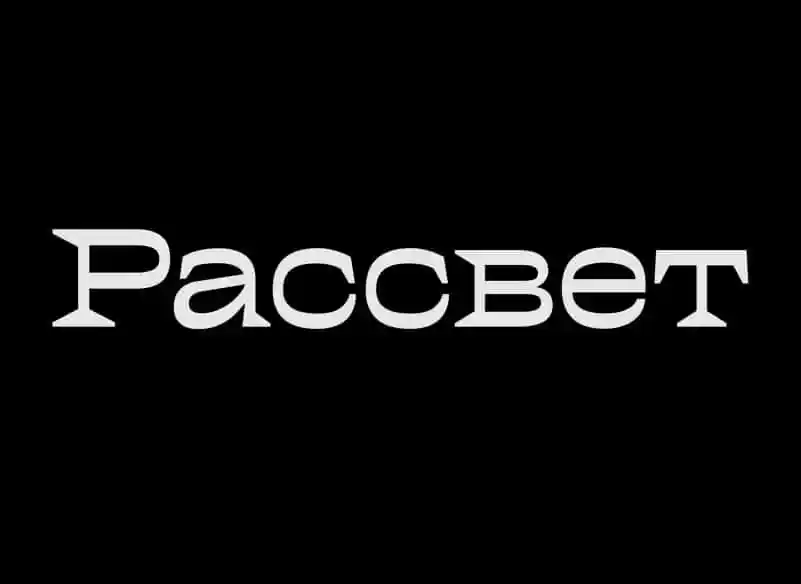
Rassvet Free Font é uma elegante serif font que transmite um ar sofisticado com um toque moderno e fluido aos seus caracteres. Ideal para qualquer tipo de projeto visual, Rassvet é perfeito para textos expressivos no design gráfico. Desenvolvida pelo designer Arthur Avtukhov, essa fonte mistura elementos vintage e futuristas em uma composição única que torna a comunicação mais atraente e envolvente. Seja você um artista de cinema criando um título para um filme ou um designer gráfico trabalhando na criação de um livro de capa, Rassvet Free Font é uma escolha perfeita. Suas opções versáteis permitem aplicação em diversas áreas, desde rótulos e material publicitário até logotipos e capas de álbuns, tornando-a indispensável para qualquer projeto criativo em que você esteja envolvido.